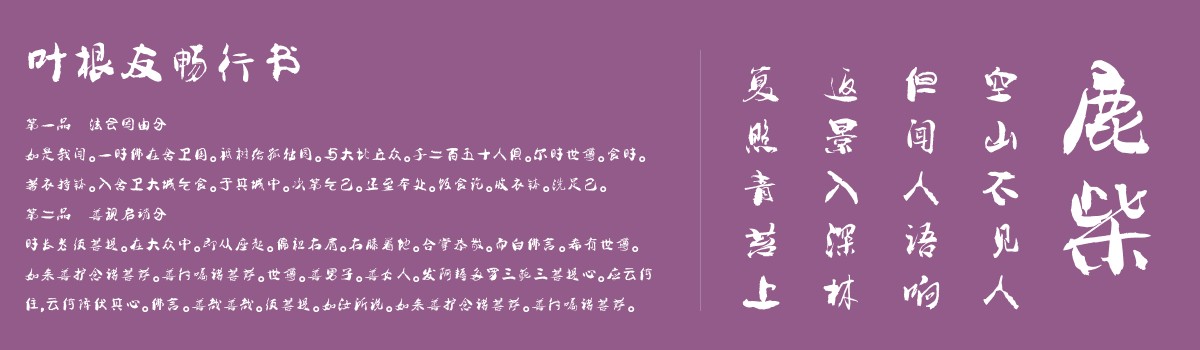
叶根友畅行书
创作年代:2015年
字体字数:6763个中文汉字以及其他英文字母和阿拉伯数字
字体介绍
叶根友畅行书是一款2015年最新创作的行书字体,这款字体是叶根友行书繁的简体风格版本,从2008年到2015年,历时七年的变化和书法风格路线的创新,叶根友的书风也引起了一定的变化,在字面上,书写的更加流畅和笔势上笔走龙蛇之轻车驾驭,在标题应用、广告标语等不错的应用选择。